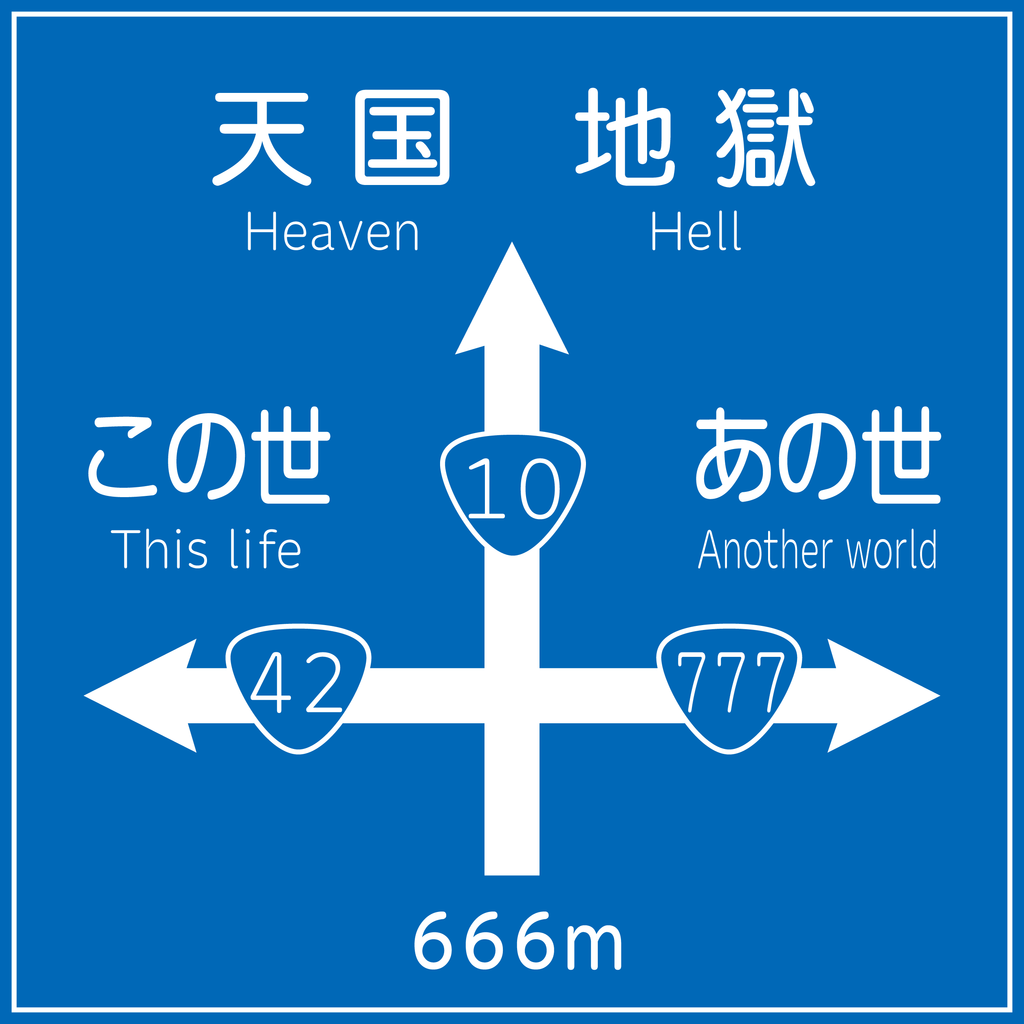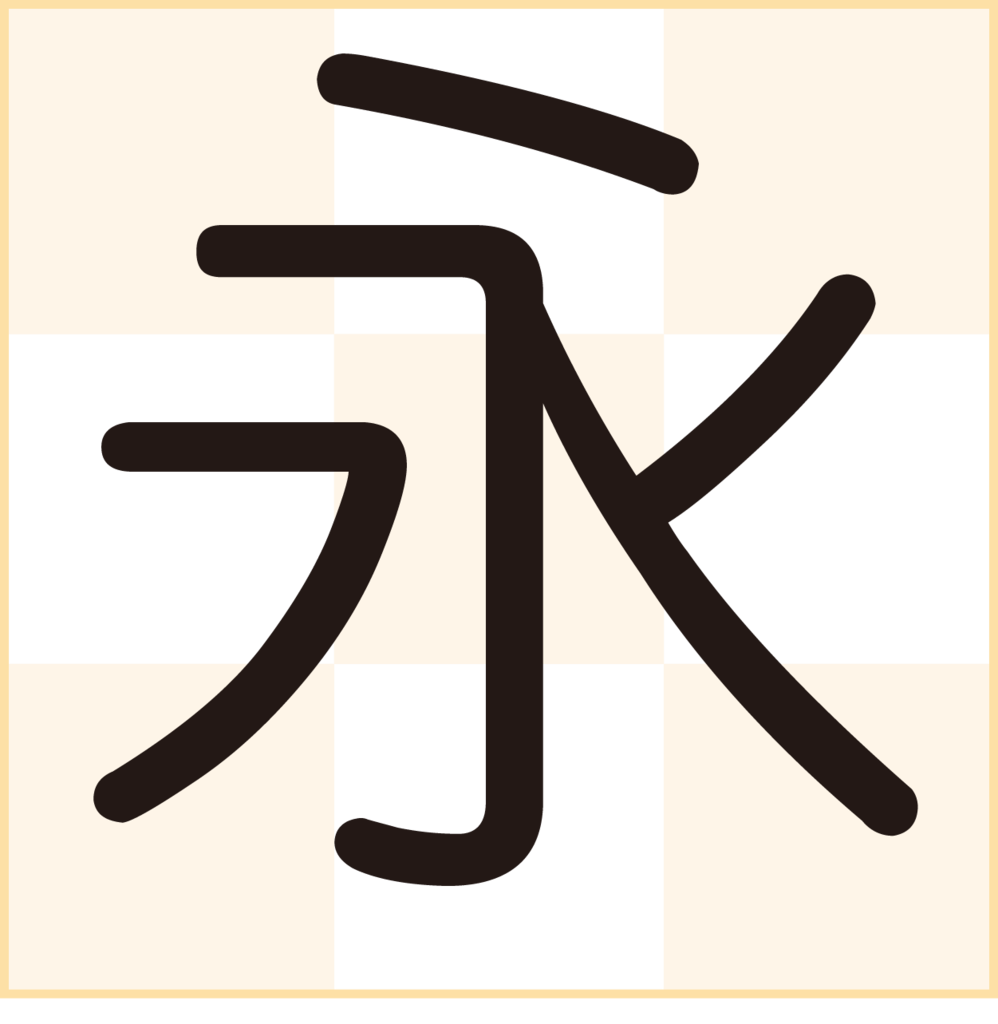
UD丸ゴシック体
「UD丸ゴシック体」は、ユニバーサルデザインをコンセプトに開発されたUDゴシック体に「丸ゴシック体」ならではの特徴を加えた柔らかい印象の書体。
新聞や取扱い説明書、約款、看板などの印刷物はもとより電子機器における表示やカーナビ、地図、スマートフォン・タブレットなどにおいても正確な情報を読みやすく伝達できる文字ツールになっている。
UD丸ゴシック体の書体見本